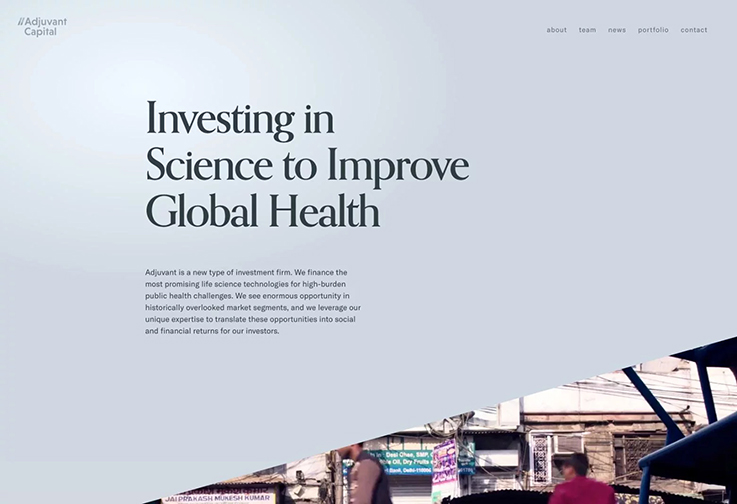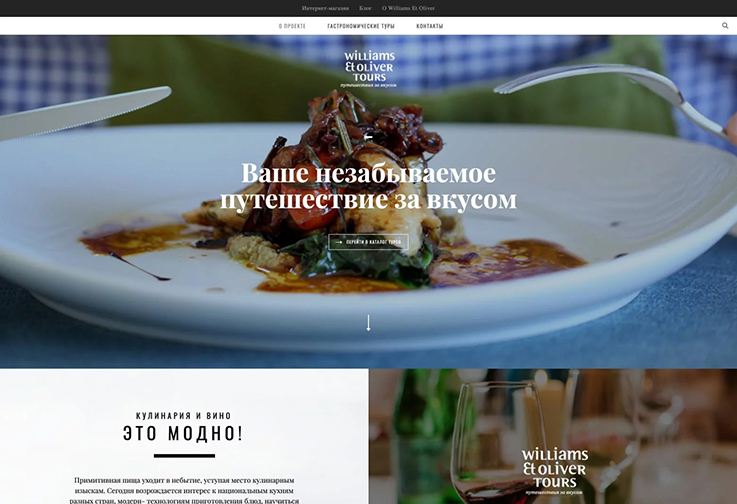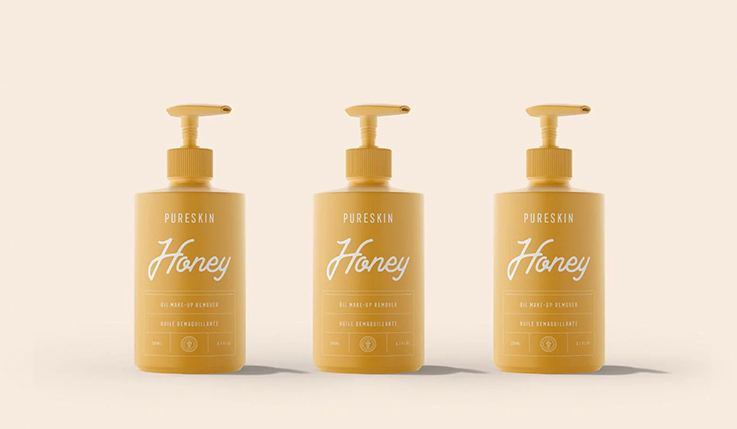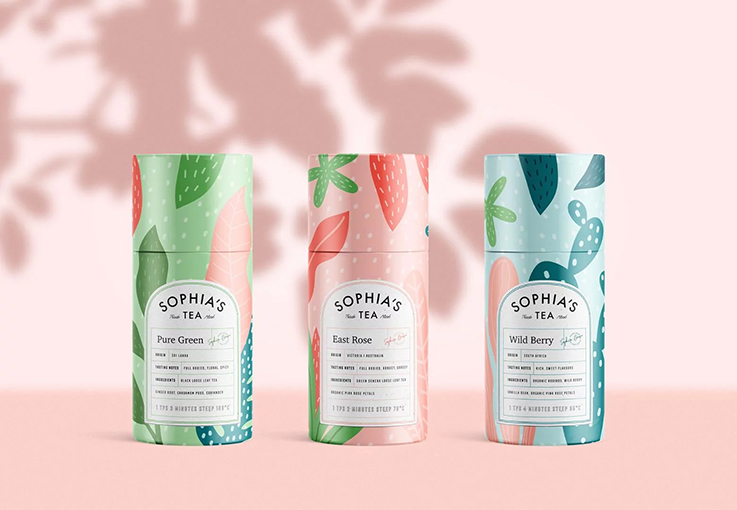
Mẹo chọn font chữ chuẩn trong thiết kế
Mẹo chọn font chữ chuẩn trong thiết kế sẽ giúp bản thiết kế của bạn thành công hơn, đẹp mắt hơn, trong khi lựa chọn font chữ sai lầm có thể phá hỏng bản thiết kế .
Việc lựa chọn font chữ trong thiết kế rất khó khăn ngay cả những nhà thiết kế chuyên nghiệp, bởi một số người có thói quen sử dụng những font chữ có sẵn mà mình thường sử dụng, hoặc có người lại mất hàng giờ để lựa chọn những font chữ mới nhưng không đạt được hiệu quả mong muốn, thậm chí lại nghi ngờ những font chữ của mình đã lựa chọn, Vì vậy mẹo để lựa chọn font chữ chuẩn trong thiết kế logo công ty hay những bản thiết kế profile, catalogue, brochure… ngoài việc bạn thực sự hiểu về mỹ thuật còn chính là cảm được cái chất mà mang công ty hướng tới, ví dụ như công ty bạn đang làm gì, ở đâu, khi nào và làm cho ai? Bạn phải tự trả lời được những câu hỏi này trước khi bắt đầu dự án thiết kế. Ngoài ra để lựa chọn cân nhắc những font chữ phù hợp ta có thể tham khảo thêm những ý kiến của các chuyên gia nhé
Phạm vi
Phạm vi của dự án hoặc các dự án trong đó một font chữ sẽ được sử dụng là một trong những điều đầu tiên các nhà thiết kế nên xem xét khi chọn một kiểu chữ. Một font chữ sẽ chỉ được sử dụng cho một phạm vi hạn chế, chẳng hạn như một bài thuyết trình thì cũng không cần phải linh hoạt như một font chữ sẽ được sử dụng thiết kế bộ nhận diện thương hiệu công ty.
Các nhà thiết kế nên suy nghĩ xem liệu kiểu chữ sẽ chỉ được sử dụng cho các dự án kỹ thuật số hay in ấn. Họ cũng nên suy nghĩ về việc các font chữ sẽ được sử dụng trong một thời gian giới hạn hay là lâu dài. Việc tạo một danh sách các dự án tiềm năng mà font chữ sẽ được sử dụng là vô cùng hữu ích trong giai đoạn đầu tiên của việc chọn lựa font chữ.
Tính chất
Mỗi dự án đều có một tâm trạng. Cho dù tâm trạng đó là chính thức hay không chính thức, vui vẻ hay nghiêm túc, hiện đại hay cổ điển, hoặc một cái gì đó hoàn toàn khác. Và giống như mọi dự án, mọi kiểu chữ đều có tâm trạng.
Nó rất quan trọng đối với các nhà thiết kế để xem xét tâm trạng của dự án và cách các kiểu chữ mà họ đang xem xét phù hợp hoặc không hợp với tâm trạng đó. Ví dụ: sử dụng Comic Sans trên một trang web cho một công ty luật sẽ không hợp. Kiểu font chữ như Crimson Text hoặc Helvetica sẽ hoạt động tốt hơn nhiều.
Chức năng
Không phải mọi kiểu chữ đều đẹp ở mọi kích cỡ. Hiển thị phông chữ trông tuyệt vời ở kích thước lớn hơn có thể trở nên không thể đọc được ở kích thước nhỏ hơn. Kiểu chữ trông tuyệt vời ở kích thước nhỏ trong văn bản cơ thể đôi khi có thể trông quá đơn giản hoặc thậm chí nhàm chán khi được sử dụng ở kích thước hiển thị.
Một số kiểu chữ có thể trông tốt ở hầu hết mọi kích thước. Các nhà thiết kế nên kiểm tra các phông chữ mà họ đang xem xét ở mỗi kích thước họ có thể sử dụng các phông chữ đó để chắc chắn rằng họ có thể đọc được.
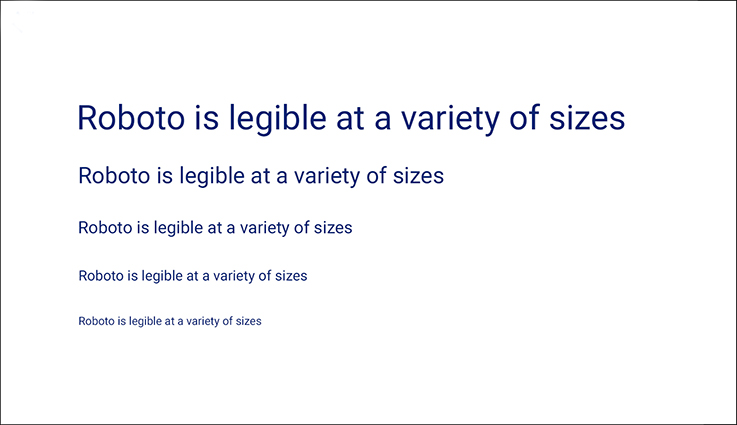
Tính linh hoạt
Các font chữ hoàn hảo để sử dụng trên web có thể không tốt để sử dụng trong in ấn và ngược lại. Các font chữ như Georgia được thiết kế dành riêng cho khả năng đọc trên màn hình độ phân giải thấp cũng không phù hợp để in tác phẩm như một font chữ như Book Antiqua.
Nếu một font chữ sẽ chỉ được sử dụng cho một dự án duy nhất, thì nó dễ dàng xác định xem chức năng in hay màn hình là quan trọng nhất. Nhưng đối với các font chữ có thể được sử dụng trong nhiều dự án, các nhà thiết kế nên đảm bảo rằng font chữ sẽ hoạt động trong mọi phương tiện có thể được sử dụng.
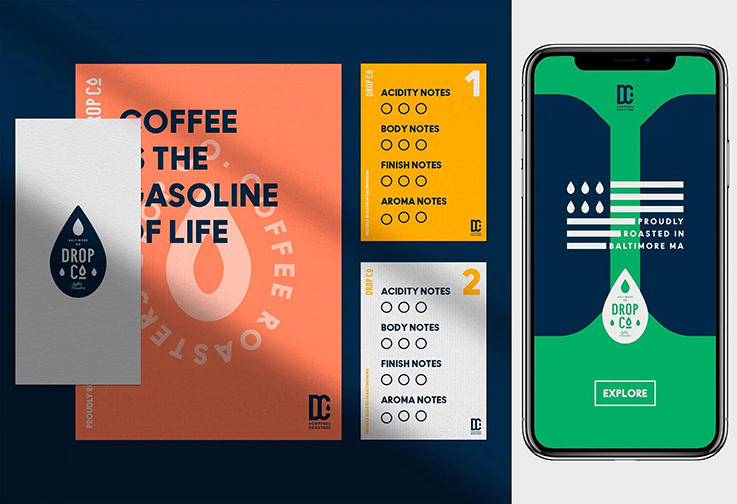
Thông điệp
Thông điệp của dự án, cho dù đó là một thuyết trình hay một nhận diện thương hiệu hình ảnh trực tuyến, rất quan trọng để xác định font chữ tốt nhất để sử dụng. Nếu thông điệp quan trọng, font chữ cũng phải nghiêm túc và ngược lại.
Font chữ sai hoàn toàn có thể làm hỏng thông điệp mà một thương hiệu đang cố gắng gửi. Ví dụ, sử dụng một cái gì đó hiện đại như Open Sans trên một thiết kế cho một trang web xã hội lịch sử không thực sự tốt. Một font chữ như Crimson Text sẽ hoạt động tốt hơn nhiều.
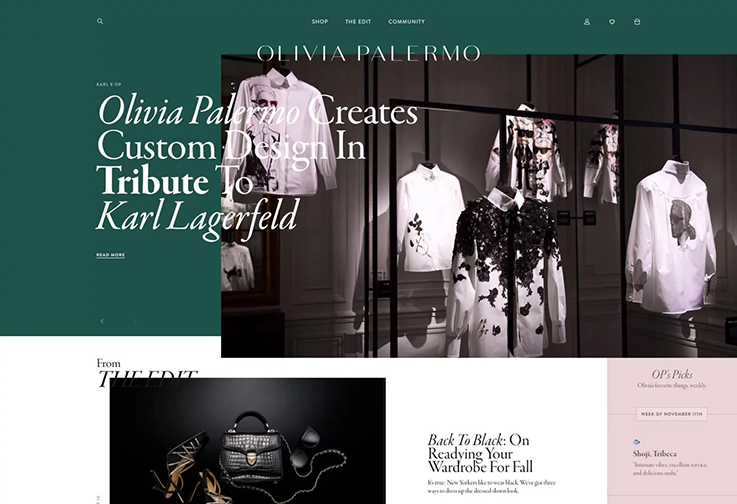
Dễ đọc
Khả năng đọc được cho là tính năng quan trọng nhất của kiểu chữ. Vì loại được sử dụng để truyền đạt một thông điệp, nếu không thể được đọc kiểu chữ đã thất bại.
Khả năng đọc và mức độ dễ đọc aren chính xác như nhau. Tính dễ đọc đề cập đến việc dễ dàng phân biệt các mẫu chữ trong một font chữ. Khả năng đọc tiến thêm một bước và đề cập đến việc có thể phân biệt và đọc các từ dễ dàng khác nhau như thế nào.
Khả năng đọc và mức độ dễ đọc đều có thể bị ảnh hưởng đáng kể bởi kích thước của font chữ được sử dụng. Một font chữ trông tuyệt vời ở 18 pixel có thể không đọc được ở 10 pixel. Rằng không nhất thiết phải là một công cụ giải quyết trừ khi người thiết kế biết font chữ sẽ cần được sử dụng ở kích thước nhỏ hơn.